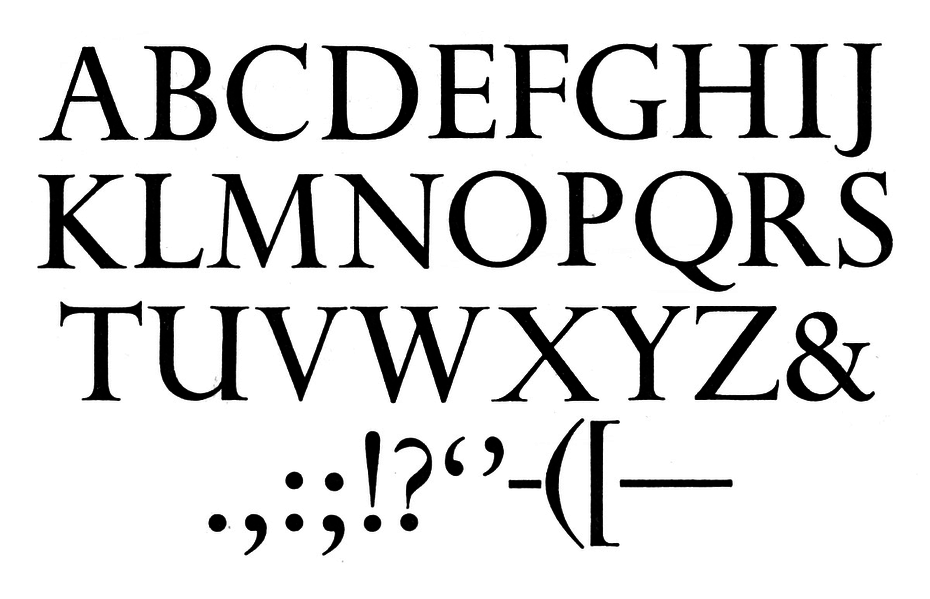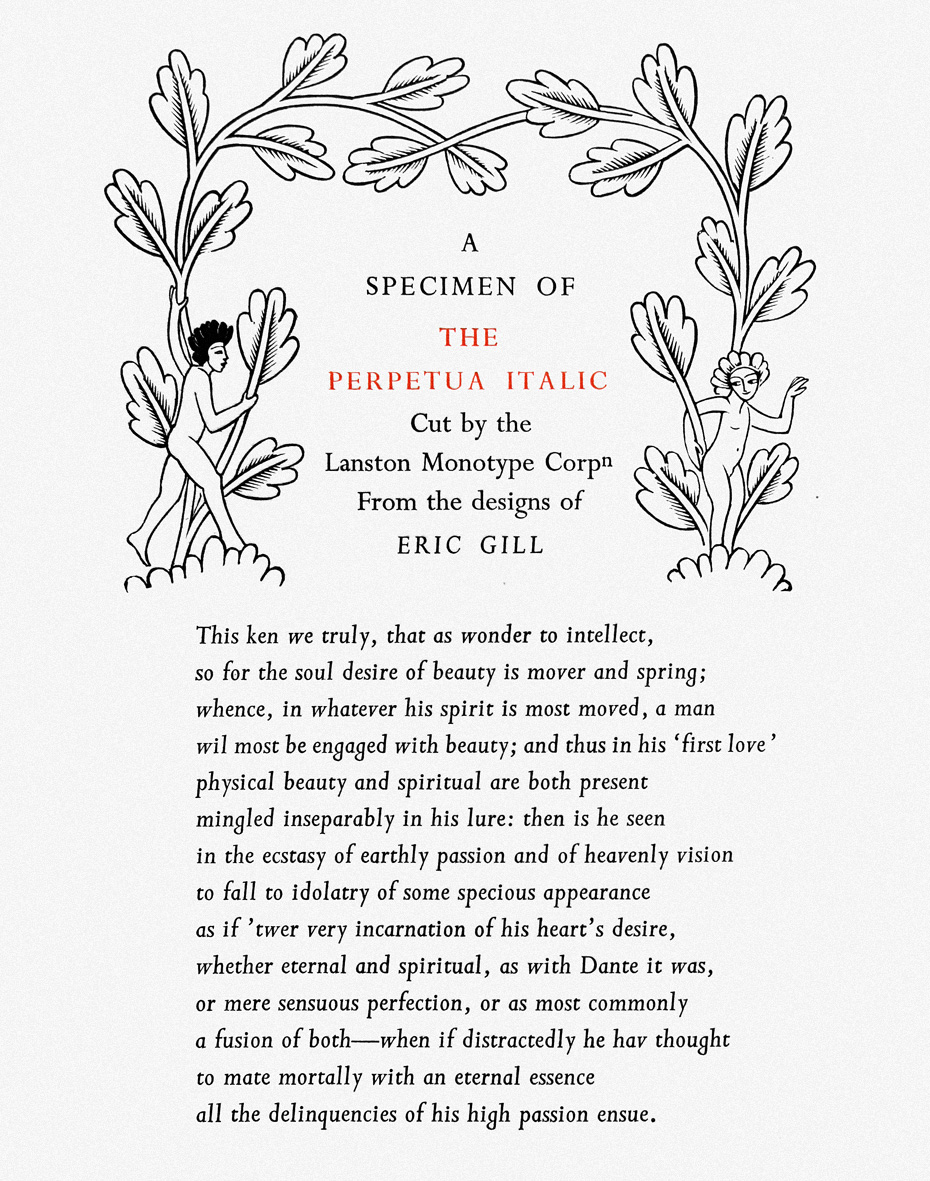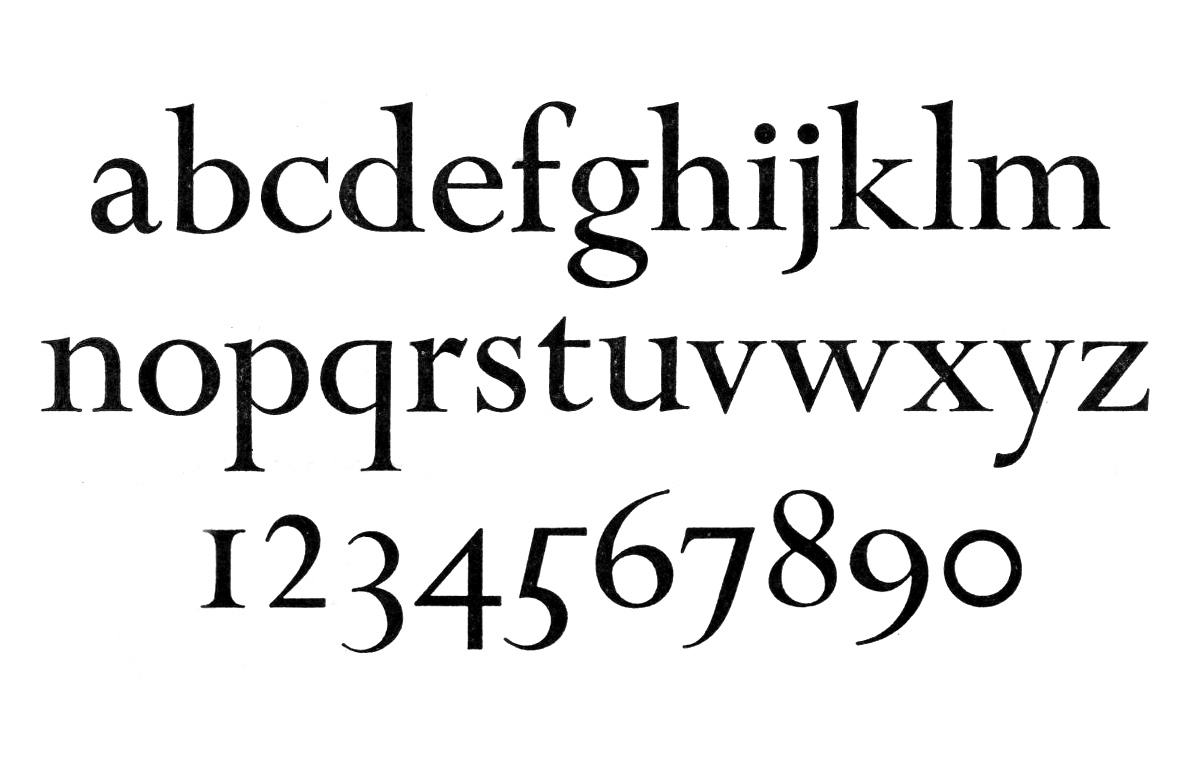
Perpetua Эрика Гилла
Пер­пе­туа — это по­сто­ян­ство, надёж­ность и вер­ность. От то­го же кор­ня про­ис­хо­дит всем из­вест­ное сло­во perpetual — «веч­ный» и зна­ме­ни­тое perpetuum mobile. Пер­пе­туа — имя хри­сти­ан­ской свя­той, рас­тер­зан­ной в Кар­фа­ге­не в III ве­ке на­шей эры. Пер­пе­туа — мыс в Ти­хом оке­а­не, на тер­ри­то­рии шта­та Оре­гон, он сла­вит­ся при­чуд­ли­во­стью при­бреж­ных скал и тан­ца­ми при­боя. Но кро­ме все­го это­го, Perpetua — шрифт Эри­ка Гил­ла, кам­не­ре­за, скуль­пто­ра, ти­по­гра­фа, гравёра и ху­дож­ни­ка, од­но­го из са­мых яр­ких и са­мо­быт­ных ав­то­ров XX ве­ка.
от са­мый шрифт, ко­то­рый сво­им ро­жде­ни­ем явил но­вый взгляд на ка­че­ство и по­треб­но­сти ти­по­гра­фи­ки XX ве­ка, опре­де­лив даль­ней­шее её раз­ви­тие. Весь цикл раз­ра­бот­ки шриф­та Perpetua в Monotype Corporation за­нял бо­лее се­ми лет — с 1925 по 1932 год. Ре­зуль­та­том этой ра­бо­ты стал об­ра­зец, не име­ю­щий пред­ше­ствен­ни­ка, эта­лон но­вой фор­мы, при­знан­ная клас­си­ка. Ра­бо­ты Ар­ту­ра Эри­ка Ро­уто­на Гил­ла (Arthur Eric Rowton Gill), его на­сле­дие, жиз­нен­ный путь и при­стра­стия — при его глу­бо­чай­шей ре­ли­ги­оз­но­сти — ста­ли объ­ек­том мно­го­чис­лен­ных ис­сле­до­ва­ний, спо­ров и да­же скандалов, а на­пи­сан­ные им днев­ни­ки и ав­то­био­гра­фия (Eric Gill: Autobiography, Jonathan Cape Ltd., London, 1939) по­тря­са­ют сте­пе­нью от­кро­ве­ния и ре­флек­сии ав­то­ра, пред­став­ляя скры­тые по­дроб­но­сти твор­че­ско­го про­цес­са.
На­ша цель — обра­тить­ся к со­бы­ти­ям и яв­ле­ни­ям ти­по­гра­фи­че­ско­го воз­ро­жде­ния на­ча­ла XX ве­ка, в ре­зуль­та­те ко­то­ро­го на свет по­явил­ся це­лый ряд уни­каль­ных при­ме­ров шриф­то­во­го ис­кус­ства, не те­ря­ю­щих свою ак­ту­аль­ность и по сей день. Го­во­ря о Perpetua, мы име­ем де­ло с фе­но­ме­наль­ны­ми та­лан­та­ми не толь­ко ху­дож­ни­ка Эри­ка Гил­ла, счи­та­ю­ще­го­ся его со­зда­те­лем, но и та­ких све­тил, как Уи­льям Мор­рис (1834–1896), Эд­вард Джон­стон (1872–1944) и Стен­ли Мо­ри­сон (1889–1967), сы­грав­ших важ­ней­шую роль в его жиз­ни и в ми­ро­вой куль­ту­ре.
В кон­це XIX ве­ка в Аме­ри­ке про­ис­хо­дит сра­зу не­сколь­ко со­бы­тий, ко­то­рые ра­ди­каль­но из­ме­нят пе­чат­ный мир. Иду­щая пол­ным хо­дом ин­ду­стри­а­ли­за­ция обес­пе­чи­ва­ет низ­кие це­ны на бу­ма­гу, а по­яв­ле­ние та­ких ин­же­нер­ных изоб­ре­те­ний, как ли­но­тип (1884) и мо­но­тип (1885), бес­пре­це­дент­но сни­жа­ет се­бе­сто­и­мость пе­ча­ти. В 1889 го­ду на про­из­вод­стве Mergenthaler Printing Co. вне­дря­ет­ся изоб­ре­те­ние Бен­то­на-стар­ше­го (Linn Boyd Benton) — пан­то­граф для ме­ха­ни­че­ско­го про­из­вод­ства мат­риц. Это при­во­дит к то­му, что кни­га ста­но­вит­ся дей­стви­тель­но мас­со­вым про­дук­том, объ­ё­мы пе­чат­ной про­дук­ции стре­ми­тель­но рас­тут, ин­ду­стрия раз­ви­ва­ет­ся се­ми­миль­ны­ми ша­га­ми.
Из­ме­не­ния на шриф­то­вом рын­ке но­си­ли так­же струк­тур­ный ха­рак­тер: уже не тре­бо­ва­лись в боль­шом ко­ли­че­стве пу­ан­со­ни­сты и на­бор­щи­ки, мел­кие сло­во­лит­ни за­кры­ва­лись, те, что по­креп­че, объ­еди­ня­лись в ак­ци­о­нер­ные об­ще­ства (в ре­зуль­та­те че­го в 1892 го­ду по­явил­ся кон­гло­ме­рат American Type Founders Company, ку­да во­шли 23 сло­во­лит­ни из 34 функ­ци­о­ни­ро­вав­ших на тот мо­мент по всей стра­не).
В это же вре­мя в ти­хой Ан­глии Уи­льям Мор­рис от­кры­ва­ет своё част­ное из­да­тель­ство Kelmscott Press (1891). На фо­не по­сред­ствен­ной пе­ча­ти, пло­хих пе­ре­плётов и низ­ко­сорт­ной бу­ма­ги мас­со­вых из­да­ний кни­ги Мор­ри­са бы­ли на­сто­я­щей дра­го­цен­но­стью. «Я на­чал из­да­вать кни­ги в на­де­жде при­бли­зить их к со­вер­шен­ной кра­со­те, со­хра­нив удо­бо­чи­та­е­мость и не от­вле­кая со­зна­ние экс­тра­ва­гант­но­стью форм букв», — пи­сал Мор­рис. Бла­го­да­ря ему в пе­чат­ном ре­ме­сле бы­ли уста­нов­ле­ны вы­со­кие стан­дар­ты, воз­ро­дил­ся ин­те­рес к ис­кус­ству кни­ги и ти­по­гра­фи­ке Ре­нес­сан­са. При­мер Мор­ри­са про­дол­жал вдох­нов­лять в те­че­ние мно­гих де­ся­ти­ле­тий не толь­ко ан­глий­ские част­ные из­да­тель­ства.
В 1897-м, че­рез де­сять лет по­сле вы­хо­да в свет мо­но­ти­пов, для их про­из­вод­ства и про­да­жи бы­ло учре­жде­но сра­зу два пред­при­я­тия Monotype: од­но в США (The Monotype Corporation), дру­гое — в Ан­глии (The Lanston Monotype Corporation). Пер­во­на­чаль­но обе ком­па­нии бы­ли ори­ен­ти­ро­ва­ны на вос­тре­бо­ван­ную рын­ком не­до­ро­гую пе­чать и га­зет­ные шриф­ты, но, под­стёги­ва­е­мые до­ми­ни­ру­ю­щим аме­ри­кан­ским кон­ку­рен­том ATF, ак­тив­ны­ми тем­па­ми при­сту­пив­шим к со­зда­нию со­вре­мен­ных шриф­тов под ру­ко­вод­ством Бен­то­на-млад­ше­го (Morris Fuller Benton), ру­ко­во­ди­те­ли Monotype осо­зна­ли не­об­хо­ди­мость серьёз­но­го пла­ни­ро­ва­ния сво­е­го шриф­то­во­го ас­сор­ти­мен­та.
Стен­ли Мо­ри­сон и со­вре­мен­ный шрифт
«Ре­ву­щие два­дца­тые» про­ка­ти­лись по все­му ми­ру яр­кой вол­ной: воз­вра­ще­ние к жиз­ни по­сле раз­ру­ши­тель­ной Пер­вой ми­ро­вой вой­ны, на­ча­ло «Эпо­хи джа­за» (The Jazz Age) в Аме­ри­ке, взрыв ис­кус­ства и ли­те­ра­тур­ной мыс­ли, ин­ду­стри­а­ли­за­ция и, как след­ствие, рост про­мыш­лен­но­го про­из­вод­ства, мас­со­вой про­дук­ции; со­ци­а­ли­сти­че­ские идеи овла­де­ва­ют ума­ми по обе сто­ро­ны Ат­лан­ти­ки. Од­ним сло­вом, мир пе­ре­вер­нул стра­ни­цу но­вей­шей ис­то­рии, что не прой­дёт бес­след­но ни для од­ной об­ла­сти че­ло­ве­че­ской де­я­тель­но­­сти.
В то вре­мя как Monotype в Фи­ла­дель­фии под ру­ко­вод­ством Фре­де­ри­ка Гау­ди вы­пус­кал но­вые ин­тер­пре­та­ции на те­му ста­рых шриф­тов, в 1920-х го­дах до­чер­няя ком­па­ния в Лон­до­не при­сту­па­ет к по­пол­не­нию сво­ей биб­лио­те­ки шриф­та­ми, ко­то­рые пред­став­ля­ли со­бой адап­та­цию клас­си­че­ских об­раз­цов руч­но­го на­бо­ра. Ме­то­дич­ная ра­бо­та по со­зда­нию но­вых шриф­тов на­би­ра­ла обо­ро­ты с не­по­сред­ствен­ным уча­сти­ем Стен­ли Мо­ри­со­на, со­вет­ни­ка по ти­по­гра­фи­ке Лон­дон­ско­го Monotype. Преж­де все­го, это бы­ла ра­бо­та по вос­кре­ше­нию та­кой ве­ко­вой клас­си­ки, как об­раз­цы ре­нес­санс­ных ан­ти­к­в Garamond (1922), Poliphilus (1923), Bembo (1929), Centaur (1929), ан­ти­кв пе­ре­ход­но­го сти­ля Baskerville (1923), Bell (1930), Fournier (1925) — мно­гие из них слу­жи­ли ве­рой и прав­дой ти­по­гра­фу не од­но сто­ле­тие. Од­на­ко для тем­пе­ра­мент­но­го XX ве­ка нуж­ны бы­ли и но­вые го­ло­са. Ис­то­рия при­го­то­вит Мо­ри­со­ну уни­каль­ную роль од­но­го из клю­че­вых участ­ни­ков воз­ро­жде­ния ти­по­гра­фи­че­ско­го де­ла XX ве­ка, а ре­зуль­та­том шриф­то­вой про­грам­мы ком­па­нии Monotype ста­нет пло­до­род­ная поч­ва для по­сле­ду­ю­ще­го успеш­но­го раз­ви­тия кор­по­ра­ции и ин­ду­стрии в це­лом.
На этой фо­то­гра­фии Стен­ли Мо­ри­сон вы­гля­дит впол­не удо­вле­творён­ным, с не­уло­ви­мы­ми при­зна­ка­ми лёг­кой улыб­ки на ли­це — со­сто­я­ние для не­го край­не ред­кое. Ча­ще все­го он за­по­ми­нал­ся лю­дям хму­рым ис­пы­ты­ва­ю­щим взгля­дом уве­рен­но­го в сво­их убе­жде­ни­ях джентль­ме­на. Веч­ное чёр­ное паль­то, чёр­ные бо­тин­ки, чёр­ный гал­стук, чёр­ная шля­па, да­же чёр­ный шну­рок на кар­ман­ных ча­сах и бе­ло­снеж­ная со­роч­ка. Го­во­рят, счаст­ли­вым его мог сде­лать толь­ко бо­кал шам­пан­ско­го за лан­чем. Од­на­ко ни од­на фо­то­гра­фия не пе­ре­даст той ис­крен­ней и тёплой ат­мо­сфе­ры, ко­то­рую он мог да­рить сво­им дру­зьям и еди­но­мыш­лен­ни­кам. Этот че­ло­век пред­по­чи­тал со­хра­нять ано­ним­ность в сво­их ини­ци­а­ти­вах, ста­вя ин­те­ре­сы це­ха пре­вы­ше пер­со­наль­ных: он знал всех, но с ним бы­ли зна­ко­мы лишь не­мно­гие. Под­чёрк­ну­тая прин­ци­пи­аль­ность убе­ждён­но­го со­ци­а­ли­ста вы­ра­зи­лась и в от­ка­зе (два­жды, в 1953 и 1962 го­дах) при­нять от мо­нар­ха почёт­ный ры­цар­ский ор­ден. Фо­то: Janet Stone © The Estate of Reynolds and Janet Stone
Вы­пол­няя обя­зан­но­сти со­вет­ни­ка по ти­по­гра­фи­ке кор­по­ра­ции Monotype, Мо­ри­сон ви­дел сво­ей за­да­чей рас­ши­ре­ние ти­по­гра­фи­че­ско­го ас­сор­ти­мен­та, ко­то­рый ис­поль­зо­вал­ся в оформ­ле­нии пе­чат­ной про­дук­ции, в том чис­ле за счёт прин­ци­пи­аль­но но­вых, со­вре­мен­ных шриф­тов. В про­фес­си­о­наль­ной жиз­ни у Стен­ли Мо­ри­со­на сло­жи­лось ис­клю­чи­тель­ное по­ло­же­ние: он был со­вет­ни­ком по ти­по­гра­фи­ке трёх ин­сти­ту­ций. По­ми­мо со­труд­ни­че­ства с Monotype Corporation в Лон­до­не он ра­бо­тал с Cambridge University Press (с 1925 го­да) и с га­зе­той The Times (с 1929-го). Связь меж­ду «Мо­но­тай­пом» и уни­вер­си­те­том Кем­бри­джа обер­ну­лась уни­каль­ной воз­мож­но­стью при­ме­нять но­вые шриф­ты сра­зу в из­да­тель­ском про­цес­се, по­лу­чая ак­тив­ную обрат­ную связь не­по­сред­ствен­но от поль­зо­ва­те­лей.
«Я на­де­юсь, в те­че­ние двух-трёх лет ан­глий­ские по­ли­гра­фи­сты до­рас­тут до пред­по­чте­ния ори­ги­наль­ных ху­до­же­ствен­ных про­из­ве­де­ний ре­про­дук­ци­ям, и это поз­во­лит убе­дить сло­во­лит­ни об­ра­щать­ся к услу­гам ху­дож­ни­ков», — пи­сал в мар­те 1926 го­да Стен­ли Мо­ри­сон Яну ван Крим­пе­ну, с ко­то­рым на про­тя­же­нии всей жиз­ни их свя­зы­вал вза­им­ный про­фес­си­о­наль­ный ин­те­рес и глу­бо­кое ува­же­ние.
За­ду­мав но­вый тек­сто­вый шрифт, Мо­ри­сон по­ни­мал, что для та­кой ра­бо­ты тре­бо­вал­ся опыт­ный ху­дож­ник, кал­ли­граф, спо­соб­ный со­здать шрифт, ко­то­рый бу­дет од­но­вре­мен­но ори­ги­на­лен и ней­тра­лен в вос­при­я­тии чи­та­те­лем. От­ме­тим, что в то вре­мя Ан­глия и Гер­ма­ния бла­го­да­ря вол­не по­сле­до­ва­те­лей Эд­вар­да Джон­сто­на и Ру­доль­фа Ко­ха (Rudolf Koch, 1876–1934) не ис­пы­ты­ва­ли не­до­стат­ка кал­ли­гра­фов и гравёров, но они прак­ти­че­ски не де­ла­ли тек­сто­вые шриф­ты, а те не­мно­го­чис­лен­ные об­раз­цы, ко­то­рые со­зда­ва­ли Коб­де­н-Сан­дер­со­н (T. J. Cobden-Sanderson), Хер­бер­т Хор­н (Herbert Horne), Чарль­з Ри­кетт­с (Charles Ricketts) и дру­гие ли­де­ры част­ных из­да­тельств, бы­ли слиш­ком вы­ра­зи­тель­ны и по­рой ма­нер­ны для по­все­мест­но­го ис­поль­зо­ва­ния в книж­ной про­дук­ции. Ис­клю­че­ни­ем мог­ли быть, по­жа­луй, шриф­ты Golden Type и Doves Type (при­над­ле­жав­шие из­да­тель­ствам Kelmscott Press и The Doves Press со­от­вет­ствен­но), со­хра­няв­шие — на фо­не осталь­ных — бла­го­род­ную ней­траль­ность, но они все­гда оста­ва­лись в экс­клю­зив­ном ис­поль­зо­ва­нии.
Та­ким об­ра­зом, ро­жде­ние Perpetua бы­ло все­це­ло ини­ци­а­ти­вой Стен­ли Мо­ри­со­на: уже то­гда он был убе­ждён, что в осно­ву но­во­го шриф­та долж­на лечь не столь­ко кал­ли­гра­фия, сколь­ко эпи­гра­фи­ка, не на­пи­сан­ное, а вы­се­чен­ное. «Знак как скульп­ту­ра» — так оха­рак­те­ри­зу­ет эту ра­бо­ту Беатрис Уорд. Из это­го сле­до­ва­ло, что с ри­сун­ком та­ко­го шриф­та луч­ше спра­вит­ся скуль­птор или кам­не­рез, в иде­а­ле не чуж­дый кал­ли­гра­фии. Эрик Гилл был и тем и дру­гим од­но­вре­мен­но. На де­ле же Мо­ри­сон, уви­дев над­пи­си, вы­се­чен­ные на кам­не ма­сте­ром и ста­рым его при­я­те­лем Гил­лом, ли­шил­ся и те­ни со­мне­ний, что шрифт дол­жен ро­дить­ся имен­но из этих вы­се­чен­ных букв. Дух вре­ме­ни был опре­делён без­оши­боч­но, и раз­ви­тие ти­по­гра­фи­че­ских тра­ди­ций XX ве­ка, по­жа­луй, бу­дет мно­гим обя­за­но это­му мо­мен­ту.
Эрик Гилл был скуль­пто­ром, книж­ным гра­фи­ком, ху­дож­ни­ком, эс­се­и­стом, фи­ло­со­фом, те­о­ре­ти­ком ти­по­гра­фи­ки и ди­зай­не­ром шриф­та. Но, по­жа­луй, глав­ным для не­го бы­ло стрем­ле­ние к чест­но­му, тру­до­во­му хри­сти­ан­ско­му жи­тию, без остат­ка под­чи­нён­но­му твор­че­ству. Не­смот­ря на шриф­то­вое на­сле­дие, име­ю­щее от­но­ше­ние к име­ни Гил­ла, он де­лал не шриф­ты, а бук­вы (что сам не­од­но­крат­но под­чёр­ки­вал). Ра­бо­тая с круп­ны­ми фор­ма­ми, будь то над­пись на над­гро­бии или ба­ре­льеф над вхо­дом в зда­ние Би-би-си, важ­ней­шим мо­мен­том он счи­тал фор­му, изоб­ражён­ную точ­но и вы­ра­зи­тель­но. Са­ми шриф­ты на осно­ве его ри­сун­ков за не­го де­ла­ли спе­ци­а­ли­сты — пу­ан­со­ни­сты или опыт­ные ху­дож­ни­ки кор­по­ра­ции Monotype. На фо­то: Эрик Гилл ра­бо­та­ет над ба­ре­лье­фом «Иисус, ис­це­ля­ю­щий сле­по­го Вар­ти­мея» для оф­таль­мо­ло­ги­че­ско­го гос­пи­та­ля в Мур­фил­дзе (Moorfields eye hospital), Лон­дон, 1934. Фо­то: Fred Morley, Getty Images
Ещё в 1914 го­ду Мо­ри­сон близ­ко сошёл­ся с Гил­лом, для че­го бы­ло не­ма­ло осно­ва­ний. Оба от­ли­ча­лись пе­дан­тиз­мом и по­сто­ян­но за­ни­ма­лись са­мо­об­ра­зо­ва­ни­ем, оба сде­ла­ли осо­знан­ный вы­бор в поль­зу ка­то­ли­циз­ма (Стен­ли в 20, Эрик в 31 год), оба раз­де­ля­ли идеи со­ци­а­лиз­ма, не­ред­ко их мож­но бы­ло за­стать за об­су­жде­ни­ем тео­ло­ги­че­ских или фи­ло­соф­ских во­про­сов. Слиш­ком мно­го сов­па­де­ний для то­го, что­бы ис­то­рия про­шла ми­мо это­го со­ю­за. И имен­но бла­го­да­ря Мо­ри­со­ну Гилл «при­ча­стил­ся» ти­по­гра­фи­ки, что по­слу­жи­ло осно­вой их даль­ней­ше­го дол­го­сроч­но­го со­труд­ни­че­ства.
От­счёт же ис­то­рии са­мо­го Perpetua мож­но на­чи­нать с но­я­бря 1925 го­да, с мо­мен­та, ко­гда Гилл дал со­гла­сие Мо­ри­со­ну на­ри­со­вать два ал­фа­ви­та в свой­ствен­ной ему ма­не­ре вы­ре­за­емых по кам­ню над­пи­сей (о чём на­сто­я­тель­но и про­сил Мо­ри­сон). Причём, как ут­вер­жда­ют ис­сле­до­ва­те­ли, Гилл от­нёс­ся к этой ра­бо­те спер­ва без осо­бо­го эн­ту­зи­аз­ма. Бо­лее то­го, го­дом ра­нее Эрик от­ка­зал Мо­ри­со­ну в на­пи­са­нии не­боль­шо­го эс­се для жур­на­ла The Fleuron со сло­ва­ми: Typography is not my country («Ти­по­гра­фи­ка — не моя сфе­ра»), а мысль о том, что его шриф­ты бу­дут ис­поль­зо­ва­ны для пе­ча­ти на со­вре­мен­ных бук­во­от­лив­ных ма­ши­нах со­глас­но всем тре­бо­ва­ни­ям ин­ду­стри­аль­ных тех­но­ло­гий, по от­но­ше­нию к ко­то­рым Гилл был на­стро­ен край­не кри­тич­но (вслед за иде­а­ла­ми дви­же­ния Уи­лья­ма Мор­ри­са Arts and Crafts), его, мяг­ко го­во­ря, не вдох­нов­ля­ла. Нуж­но от­дать долж­ное Мо­ри­со­ну, ко­то­рый про­явил де­ли­кат­ность и так­тич­ность в убе­жде­нии. Ему ну­жен был имен­но Гилл, спо­соб­ный, как род­ствен­ная ду­ша, в со­вер­шен­стве по­нять и во­пло­тить за­мы­сел. На тре­тий день по­сле на­стой­чи­вых пред­ло­же­ний Мо­ри­со­на Гилл опре­де­лил сто­и­мость из рас­чёта 10 фун­тов за день ра­бо­ты и сел за ри­сун­ки. 26 но­я­бря 1925 го­да в своём днев­ни­ке за­пи­шет: «Ditto, all day long».
Ал­фа­вит и циф­ры Эри­ка Гил­ла (1909 год), ко­то­рые он вы­сек в ка­че­стве об­раз­цов для ис­поль­зо­ва­ния школь­ни­ка­ми и ре­ме­слен­ни­ка­ми в ра­бо­те с тек­ста­ми и за­го­лов­ка­ми (Manuscript and inscription lettering for schools and classes and for use of craftsmen) и под­го­то­вил сов­мест­но со сво­им учи­те­лем и на­став­ни­ком Эд­вар­дом Джон­сто­ном. Это ти­пич­ные для Гил­ла фор­мы, ко­то­рые най­дут от­ра­же­ние в кам­не, на бу­ма­ге и в ко­неч­ном счёте по­па­дут в бук­во­от­лив­ные ма­ши­ны. Се­го­дня эти дос­ки хра­нят­ся в Му­зее Вик­то­рии и Аль­бер­та (Victoria & Albert Museum) в Лон­до­не. Фо­то: Jo De Baerdemaeker, Лон­дон, 2008.
План Стен­ли Мо­ри­со­на по раз­ра­бот­ке со­вре­мен­но­го ди­зай­на шриф­та, не име­ю­ще­го кон­крет­но­го ис­то­ри­че­ско­го про­то­ти­па, но вос­хо­дя­ще­го к мно­го­ве­ко­вым куль­тур­ным тра­ди­ци­ям, со­сто­ял в сле­ду­ю­щем: по­сле то­го как Гилл за­вер­шит ра­бо­ту с ри­сун­ка­ми зна­ков, са­ми ли­те­ры долж­ны бы­ли ро­дить­ся не в тех­но­ло­ги­че­ских не­драх ком­па­нии Monotype с при­ме­не­ни­ем ме­ха­ни­че­ско­го пан­то­гра­фа, а в опыт­ных ру­ках на­сто­я­ще­го ма­сте­ра, ко­им был вы­бран пу­ан­со­нист, па­ри­жа­нин Шарль Ма­лен (Charles Malin, 1883–1955), один из луч­ших в своём де­ле, ре­ко­мен­до­ван­ный Мо­ри­со­ну фран­цуз­ским ти­по­гра­фом Фран­с­уа Ти­ба­ду (François Thibaudeau, 1860–1925). Та­ким об­ра­зом, сам мо­мент ро­жде­ния со­вре­мен­но­го шриф­та Perpetua рев­ност­но огра­ждал­ся от вли­я­ния но­вых тех­но­ло­гий и уча­стия со­труд­ни­ков ком­па­нии Monotype. По сво­ей су­ти и мо­де­ли шрифт Perpetua сре­ди со­вре­мен­ни­ков, про­из­ведён­ных меж­ду дву­мя ми­ро­вы­ми вой­на­ми, явил­ся бли­жай­шим к шриф­там Уи­лья­ма Кэз­ло­на и Джо­на Бас­кер­ви­ля, при этом со­че­тая в се­бе од­но­вре­мен­но при­зна­ки ан­тикв как нео­клас­си­циз­ма, так и ре­нес­санс­ных.
Perpetua хра­нит в се­бе од­но­вре­мен­но основ­ные при­зна­ки пе­ре­ход­ной и ста­ро­стиль­ной ан­тикв. С од­ной сто­ро­ны — сме­ше­ние в строч­ных зна­ках вер­ти­каль­ных осей ова­лов в бук­ве «о» с ди­на­ми­кой штри­хов в по­луо­ва­лах и спин­ках «с» и «е», до­ста­точ­но вы­со­кий кон­траст, ре­гу­ляр­ная ши­ри­на строч­ных зна­ков и вы­гра­ви­ро­ван­ные утон­чён­ные верх­ние и ниж­ние за­сеч­ки. С дру­гой — уме­рен­ная вы­со­та строч­ных зна­ков (x-height), за­мет­но удлинён­ные вы­нос­ные эле­мен­ты, в осо­бен­но­сти ниж­ние, что вы­ну­жда­ет на­би­рать текст с бóль­шим меж­строч­ным ин­тер­ва­лом, и, ко­неч­но, яв­ная раз­но­ши­рин­ность про­пис­ных зна­ков, что ука­зы­ва­ет на осмыс­ле­ние на­сле­дия рим­ских мо­ну­мен­таль­ных над­пи­сей и тра­ди­ции ста­ро­стиль­ных ан­тикв.
Эрик, или Ма­ло-по­ма­лу
Хо­тя Эрик Гилл ни­ко­гда не был про­фес­си­о­наль­ным шриф­то­вым ди­зай­не­ром, бук­вы со­про­во­жда­ли его с ран­ней юно­сти до са­мой кон­чи­ны. Он пи­сал бук­вы ки­стью и пе­ром, гра­ви­ро­вал на де­ре­ве и — что бы­ло основ­ным его за­ня­ти­ем — вы­се­кал на кам­не. Ка­мень был его дру­гом, со­рат­ни­ком, кор­мив­шим его всю жизнь. Се­го­дня под­счи­та­но, что он соб­ствен­но­руч­но из­го­то­вил не ме­нее пя­ти­сот со­ро­ка пя­ти мо­ну­мен­таль­ных над­пи­сей, в основ­ном на над­гро­би­ях. Это он и счи­тал сво­ей про­фес­си­ей. Над­пись на его соб­ствен­ном над­гро­бии, под­го­тов­лен­ном им при жиз­ни и вы­пол­нен­ном уже уче­ни­ка­ми, гла­сит: «Мо­ли­тесь за кам­не­ре­за Эри­ка Гил­ла».
Над­пись на над­гро­бии Эри­ка Гил­ла (на бап­тист­ском клад­би­ще у цер­кви Speen Church в не­боль­шой де­ре­вуш­ке Chiltern Hills в юго-вос­точ­ной ча­сти Ан­глии): Pray for me. Eric Gill. Stone Carver (1882–1940). And for my most dear wife Mary Ethel (1878–1961). Фо­то: Ben Jones, 2012
Эрик Гилл ро­дил­ся 22 фе­вра­ля 1882 го­да в Брай­то­не, в се­мье ан­гли­кан­ско­го свя­щен­ни­ка. Се­мья Гил­лов бы­ла боль­шая и друж­ная, вос­пи­тан­ная в лю­бви, тру­де и стро­гих пра­ви­лах вик­то­ри­ан­ской мо­ра­ли. Да­же име­на всех три­на­дца­ти де­тей бы­ли им да­ны в честь ге­ро­ев сен­ти­мен­таль­ных нра­во­учи­тель­ных ро­ма­нов. В част­но­сти, сам Эрик Гилл обя­зан сво­им име­нем кни­ге «Эрик, или Ма­ло-по­ма­лу», где ге­рой, обра­тив­шись к Бо­гу, пре­одо­ле­ва­ет празд­ность и по­ро­ки.
По сви­де­тель­ству од­но­го из био­гра­фов, отец Эри­ка Гил­ла на­учил сы­на двум важ­ным ве­щам: стра­ху Бо­жье­му и пра­виль­ной очин­ке ка­ран­да­шей. От­ме­ча­лось так­же, что всю свою жизнь Гилл, по су­ти, ис­кал сов­па­де­ния со сво­им вну­трен­ним иде­а­лом чест­но­го, оду­хо­творён­но­го, твор­че­ско­го тру­да, для ко­то­ро­го нет ни­че­го вто­ро­сте­пен­но­го, не­важ­но­го и низ­ко­го. Имен­но стрем­ле­ние жить бо­го­угод­но при­ве­ло Эри­ка Гил­ла в хри­сти­ан­скую тру­до­вую ком­му­ну в де­рев­не Дит­члинг (Ditchling) близ Брай­то­на, где его рас­ту­щая се­мья — же­на Этель, три до­че­ри и приём­ный сын — про­ве­ла сем­на­дцать лет. Тем не ме­нее, как это слу­ча­ет­ся с твор­че­ски­ми и ак­тив­ны­ми людь­ми, меж­ду Гил­лом и осталь­ным со­об­ще­ством со вре­ме­нем воз­ник­ли раз­но­гла­сия, при­вед­шие к раз­ры­ву. В 1913 го­ду сам Гилл и его же­на (сме­нив­шая при этом имя Этель на Мэ­ри) пе­ре­шли в ка­то­ли­че­ство. Иде­а­лы дви­же­ния Arts and Crafts, стре­мив­ше­го­ся на­пол­нить ис­кус­ством и кра­со­той по­все­днев­ную жизнь, бы­ли близ­ки и Гил­лу, а как че­ло­век тру­дя­щий­ся, он не мог при этом не раз­де­лять со­ци­а­ли­сти­че­ских взгля­дов. Не­смот­ря на то что Мор­рис ушёл из жиз­ни, ко­гда Гилл был две­на­дца­ти­лет­ним школь­ни­ком, род­ство их взгля­дов и су­жде­ний — вне вся­ких со­мне­ний. В очер­ке «Уи­льям Мор­риc и Эрик Гилл» Пе­те­ра Фолк­не­ра (Willam Morris and Eric Gill, Peter Faulkner, 1975) под­чёр­ки­ва­ет­ся, что сре­ди мно­же­ства по­сле­до­ва­те­лей Мор­ри­са имен­но Эрик Гилл вобрал в се­бя уни­каль­ную ком­би­на­цию ху­дож­ни­ка и кри­ти­ка, ре­ме­слен­ни­ка и мыс­ли­те­ля.
Свою са­мо­сто­я­тель­ную жизнь Эрик Гилл на­чал с изу­че­ния ар­хи­тек­ту­ры и прак­ти­ки в ар­хи­тек­тур­ной ма­стер­ской в Лон­до­не. Но вро­ждён­ная до­бро­со­вест­ность и стрем­ле­ние про­ник­нуть в суть ве­щей при­ве­ли его так­же в класс резь­бы по кам­ню, а лю­бовь и ин­те­рес к бук­вам — к та­ин­ствам кал­ли­гра­фи­че­ско­го ма­стер­ства. К это­му же лон­дон­ско­му пе­ри­о­ду от­но­сят­ся его пер­вые уче­ни­че­ские и за­каз­ные гра­вю­ры по де­ре­ву. На­чи­ная с этих лет Гилл как гра­фик-ил­лю­стра­тор ак­тив­но со­труд­ни­чал с част­ны­ми из­да­тель­ства­ми, круг его кон­так­тов был пло­до­тво­рен и ши­рок. Наи­бо­лее силь­ное вли­я­ние на Гил­ла в те го­ды ока­зал Эд­вард Джон­стон (Edward Johnston, 1872–1944) — кал­ли­граф, пре­по­да­ва­тель, те­о­ре­тик и прак­тик шриф­та и ти­по­гра­фи­ки.
Кро­ме да­ра ис­кус­но­го кал­ли­гра­фа, Эд­вард Джон­стон, не­смот­ря на сла­бое здо­ро­вье, об­ла­дал ис­кря­щим­ся та­лан­том ма­сте­ра-про­по­вед­ни­ка, сот­ни его одарён­ных сту­ден­тов и по­сле­до­ва­те­лей раз­де­ля­ли его цен­но­сти и убе­жде­ния. Гилл вспо­ми­нал пер­вое впе­чат­ле­ние от зна­ком­ства с бу­ду­щим учи­те­лем и на­став­ни­ком так: «Я был сражён све­том… Ко­гда я в пер­вый раз уви­дел его за ра­бо­той и уви­дел его кал­ли­гра­фию, ме­ня охва­ти­ла дрожь и то не­за­бы­ва­е­мое ощу­ще­ние, ко­то­рое мо­жет воз­ник­нуть толь­ко при пер­вом ка­са­нии к жен­ско­му те­лу». На этой фо­то­гра­фии, сде­лан­ной в 1902 го­ду, Джон­сто­ну 30 лет. Имен­но в этот пе­ри­од его для се­бя от­кры­ва­ет два­дца­ти­лет­ний Эрик. По­зд­нее у них бу­дет до­ста­точ­но по­во­дов для пло­до­твор­ной ра­бо­ты. Ана­лиз шриф­то­вых и кал­ли­гра­фи­че­ских форм, на­чи­ная с ан­тикв Perpetua и Golden Cockerel и за­кан­чи­вая гу­ма­ни­сти­че­ским гро­те­ском Gill Sans, убе­дит ис­сле­до­ва­те­ля в том, что ис­точ­ник от­но­ше­ния Эри­ка Гил­ла к фор­ме, его взгляд на прин­ци­пы, кон­струк­ции и пла­сти­ку шриф­та оче­ви­ден — это Эд­вард Джон­стон.
Имя Джон­сто­на свя­за­но с глу­бо­ким ана­ли­зом и пе­ре­осмыс­ле­ни­ем тех­ни­ки и прин­ци­пов кал­ли­гра­фии. Изу­чая сред­не­ве­ко­вые ру­ко­пи­си в Бри­тан­ском му­зее, он вер­нул ин­те­рес к ши­ро­ко­ко­неч­но­му пе­ру для це­лой пле­я­ды кал­ли­гра­фов (как в Ан­глии, так и в Гер­ма­нии). В кни­ге Writing & Illuminating & Lettering (Published by John Hogg, London, 1906) Джон­стон за­фик­си­ро­вал и си­сте­ма­ти­зи­ро­вал свои клю­че­вые на­блю­де­ния в от­но­ше­нии эво­лю­ции ев­ро­пей­ских по­чер­ков, по­дроб­но опи­сал вли­я­ние ин­стру­мен­та на об­раз бук­вы, со свой­ствен­ной ему пе­дан­тич­но­стью пред­ста­вил как струк­ту­ру зна­ков ла­тин­ско­го ал­фа­ви­та, так и тех­но­ло­гию оформ­ле­ния и из­го­тов­ле­ния кни­ги. Мож­но ска­зать, Джон­стон со­здал «учеб­ник хо­ро­ших ма­нер и вы­со­ко­го вку­са» по оформ­ле­нию кни­ги. Этот труд сра­зу же был пе­ре­ведён на не­мец­кий язык его сту­дент­кой Ан­ной Си­монс (Anna Simons) и из­дан в Лейп­ци­ге в 1910 го­ду.
Вли­я­ние Эд­вар­да Джон­сто­на не толь­ко сы­гра­ло су­ще­ствен­ную роль в об­ла­сти про­фес­си­о­наль­но­го ин­те­ре­са Гил­ла, кал­ли­гра­фии и лет­те­рин­га — оно це­ли­ком из­ме­ни­ло его об­раз мыс­ли, его ми­ро­воз­зре­ние и жиз­нен­ные це­ли. Пе­ре­няв от учи­те­ля на­вы­ки и страсть к со­вер­шен­ству фор­мы, Гилл при­ме­нил своё ма­стер­ство в резь­бе по кам­ню. Имен­но на за­ня­ти­ях Эд­вар­да Джон­сто­на Эрик Гилл впер­вые по­лу­чит глу­бо­кое пред­став­ле­ние о рим­ском мо­ну­мен­таль­ном пись­ме и ана­то­мии зна­ков ко­лон­ны Тра­я­на, изу­чив прин­ци­пы ко­то­рых он смо­жет пред­ло­жить свой взгляд на эти бук­вы.
«Бу­ду­чи сту­ден­том я изу­чал рим­ские мо­ну­мен­таль­ные над­пи­си, но с тех пор, как я стал про­фес­си­о­наль­но за­ни­мать­ся над­пи­ся­ми на над­гроб­ных кам­нях, я по­нял, на­сколь­ко бы­ло бы не­ра­зум­но ко­пи­ро­вать ста­рые мо­де­ли бук­валь­но. Я го­во­рил сво­им под­ма­сте­рьям, пи­сал в кни­гах и по­вто­рял на лек­ци­ях бес­счёт­ное ко­ли­че­ство раз: мы долж­ны со­зда­вать об­раз на­ше­го вре­ме­ни, по­ла­га­ясь на ра­зум и ма­стер­ство», — пи­сал Эрик Гилл в 1934 го­ду.
Тем не ме­нее, слож­но удер­жать­ся от срав­не­ния Perpetua со шриф­том Тра­я­но­вой ко­лон­ны. Здесь и там — ты­ся­чи букв на кам­не, вы­ве­рен­ные го­да­ми приё­мы ра­бо­ты, де­та­ли и про­пор­ции, по­стро­ен­ные на прин­ци­пах кру­га и квад­ра­та. Но тем оче­вид­нее и важ­нее раз­ли­чия. Мо­ну­мен­таль­ные над­пи­си ан­тич­но­сти пред­ста­ва­ли взо­ру под яр­ким солн­цем, на рас­сто­я­нии до де­сят­ков мет­ров. Оче­вид­но, что ди­стан­ция меж­ду зри­те­лем и над­гроб­ным кам­нем на­мно­го мень­ше, что даёт ви­деть бли­же и де­та­ли. Не­смот­ря на об­щую при­ро­ду ре­зуль­та­та — след на кам­не — в осно­ве шриф­тов ле­жат раз­ные тех­ни­ки ис­пол­не­ния. Из­вест­но, что, преж­де чем вы­сечь рим­ские мо­ну­мен­таль­ные над­пи­си, кам­не­ре­зы на­но­си­ли их с по­мо­щью ши­ро­кой ки­сти, впо­след­ствии вы­се­кая рез­цом. От­сю­да и плав­ность штри­хов и за­се­чек, мяг­кая ди­на­ми­ка окруж­но­стей и об­щая по­дат­ли­вость фор­мы. Мо­жем пред­по­ло­жить, что Эрик Гилл по­ла­гал­ся на зу­би­ло, пред­став­ляя, ка­ким об­ра­зом фор­ма бу­дет до­бы­вать­ся из кам­ня. Здесь не остаёт­ся про­стран­ства для ва­ри­а­ций сле­да ки­сти, праг­ма­ти­ка ин­стру­мен­та дик­ту­ет вы­ве­рен­ные ра­ци­о­наль­ные дви­же­ния. За­сеч­ка ста­но­вит­ся бо­лее од­но­знач­ной оста­нов­кой штри­ха, кон­траст в зна­ках уве­ли­чи­ва­ет­ся, оси ова­лов прак­ти­че­ски ли­ша­ют­ся ди­на­ми­ки, при этом не те­ряя свя­зи с дви­же­ни­я­ми ру­ки. Ре­зуль­тат про­из­во­дит впе­чат­ле­ние ра­зум­но­го и по­сле­до­ва­тель­но­го пе­ре­ло­же­ния тра­ди­ции в но­вую фор­му.
Эрик Гилл был вос­при­им­чив к ра­бо­те сво­е­го стар­ше­го кол­ле­ги Джон­сто­на и пе­дан­тич­но сле­до­вал по­лу­чен­ным уро­кам, овла­дев ма­стер­ством кал­ли­гра­фа. Кон­струк­ции зна­ков, пла­сти­че­ские осо­бен­но­сти от­дель­ных эле­мен­тов букв, про­пор­ции — всё на­хо­дит­ся в уди­ви­тель­ном со­гла­сии с об­раз­ца­ми Джон­сто­на. По­очерёд­ное срав­не­ние ра­бо­т Джон­сто­на и Гил­ла вы­яв­ля­ет прин­ци­пы, ко­то­рым сле­до­вал Гилл и в сво­ей кал­ли­гра­фии, и в сво­их шриф­тах: это свое­об­раз­ное со­вер­шен­ство­ва­ние, от­та­чи­ва­ние джон­сто­нов­ской фор­мы, все ха­рак­тер­ные чер­ты зна­ков (на­при­мер, a, f, p, q, r, циф­ры) по­сле­до­ва­тель­но не­из­мен­ны. ДНК этих форм не по­ки­нет Гил­ла всю его жизнь и бу­дет пе­ре­да­вать­ся от шриф­та к шриф­ту.
Perpetua и Felicity на пе­чат­ном стан­ке
Perpetua впер­вые бы­ла пред­став­ле­на зри­те­лю в фи­наль­ном, седь­мом вы­пус­ке жур­на­ла The Fleuron, вы­хо­див­шем к то­му мо­мен­ту под ре­дак­ци­ей Стен­ли Мо­ри­со­на, в 1930 го­ду. Спе­ци­аль­ной вклад­кой в жур­нал на уплот­нён­ной бу­ма­ге шриф­том Perpetua в три­на­дца­том кегле был на­бран текст «Стра­сти Пер­пе­туи, Фе­ли­ци­та­ты и с ни­ми по­стра­дав­ших», со­про­во­ждав­ший­ся тре­мя кси­ло­гра­фи­я­ми, вы­ре­зан­ны­ми са­мим Эри­ком спе­ци­аль­но для это­го из­да­ния. Пла­сти­че­ская связь шриф­та и кси­ло­гра­фий, вы­пол­нен­ных од­ной ру­кой, со­зда­ют гар­мо­нич­ный и бла­го­род­ный эф­фект книж­ной стра­ни­цы, под стать са­мо­му тек­сту. Ду­ма­ет­ся, этот об­ра­зец мог бы по­явить­ся в ка­че­стве до­стой­но­го при­ме­ра един­ства про­доль­ной гра­вю­ры и тек­сто­во­го шриф­та в гла­ве «О шриф­те» Вла­ди­ми­ра Фа­вор­ско­го, со­вре­мен­ни­ка и по­чти ро­вес­ни­ка Эри­ка Гил­ла.
Жур­нал The Fleuron вы­хо­дил в Лон­до­не с 1923 по 1930 го­д. Все­го за это вре­мя бы­ло вы­пу­ще­но семь но­ме­ров. Эти объ­ём­ные из­да­ния в твёр­дом пе­ре­плёте, фор­ма­том с до­брый том эн­цик­ло­пе­дии слож­но на­звать жур­на­лом. Пер­вые че­ты­ре но­ме­ра вы­шли под ре­дак­ци­ей Оли­ве­ра Сай­мо­на (Oliver Simon), по­след­ние три — под ре­дак­ци­ей Стен­ли Мо­ри­со­на. The Fleuron пуб­ли­ко­вал по­дроб­ные очер­ки и ста­тьи о шриф­то­вом ди­зай­не, ти­по­гра­фи­ке, на его стра­ни­цах по­яв­ля­лись об­зо­ры ра­бот ти­по­гра­фов, об­раз­цы книж­но­го ис­кус­ства и скру­пулёз­ные шриф­то­вые ре­цен­зии. Бла­го­да­ря это­му жур­нал бы­стро снис­кал ува­же­ние и стал вли­я­тель­ным из­да­ни­ем да­ле­ко за пре­де­ла­ми Ан­глии. Седь­мой но­мер (где и бы­ла пред­став­ле­на чи­та­те­лю Perpetua) стал по­след­ним: не­смот­ря на мно­го­чис­лен­ные прось­бы чи­та­те­лей и кол­лег, Стен­ли Мо­ри­сон при­нял ре­ше­ние пре­кра­тить вы­пуск жур­на­ла. С од­ной сто­ро­ны, жур­нал от­ни­мал не толь­ко все его си­лы (ко­то­рые к то­му мо­мен­ту бы­ли бо­лее чем вос­тре­бо­ва­ны в раз­ных про­ек­тах), но и сред­ства: про­из­вод­ство каж­до­го но­ме­ра об­хо­ди­лось в круг­лую сум­му; с дру­гой — ко­ли­че­ство тем и ав­то­ров, спо­соб­ных пи­сать для жур­на­ла, как под­чёр­ки­вал Мо­ри­сон, бы­ло очень огра­ни­чен­но.
Пе­ред пре­ди­сло­ви­ем к этой вклад­ке по­ме­ще­на за­пис­ка Эри­ка Гил­ла, в ко­то­рой го­во­рит­ся сле­ду­ю­щее: «Шрифт Perpetua, ко­то­рым на­бран этот пе­ре­вод в ка­че­стве пер­во­го об­раз­ца ис­поль­зо­ва­ния, был из­го­тов­лен кор­по­ра­ци­ей Lanston Monotype на осно­ве ри­сун­ков ал­фа­ви­та, сде­лан­ных мною. Эти ри­сун­ки име­ли ма­лое от­но­ше­ние к са­мой ти­по­гра­фи­ке, это бы­ли про­сто бук­вы, на­ри­со­ван­ные ки­стью и ту­шью. За ка­че­ство шриф­та, так же как и за весь­ма точ­ное ис­пол­не­ние пу­ан­со­нов, дóлж­но бла­го­да­рить Monotype Corporation. По мо­е­му мне­нию, Perpetua, не­смот­ря на мно­же­ство яр­ких осо­бен­но­стей, со­хра­ня­ет опре­делён­ную обы­ден­ность и ней­траль­ность, столь не­об­хо­ди­мые хо­ро­ше­му книж­но­му шриф­ту».
На удив­ле­ние, в этих сло­вах Гил­ла не на­шлось ме­ста при­зна­тель­но­сти Мо­ри­со­ну, не­смот­ря на то что тот не толь­ко ини­ци­и­ро­вал раз­ра­бот­ку это­го шриф­та, сфор­му­ли­ро­вав основ­ной за­прос, но и тща­тель­но опе­кал про­ект на всех ста­ди­ях. Он вы­сту­пал свое­об­раз­ным мо­стом меж­ду са­мим Гил­лом и пу­ан­со­ни­стом Шар­лем Ма­ле­ном, а за­тем и ди­зай­не­ра­ми «Мо­но­тай­па». Не упо­ми­на­ет­ся и роль пу­ан­со­ни­ста, ко­то­рый с вы­со­ты сво­е­го опы­та и со­здал од­но­род­ный и гар­мо­нич­ный шрифт на осно­ве ри­сун­ков Гил­ла, вно­ся в про­цес­се ра­бо­ты важ­ные из­ме­не­ния в де­та­ли и про­пор­ции зна­ков. К при­ме­ру, при­слав оче­ред­ную про­бу вы­ре­зан­ных зна­ков, Ма­лен в со­про­во­ди­тель­ной за­пис­ке Мо­ри­со­ну (13 мая 1926 го­да) пи­шет сле­ду­ю­щее: «С боль­шим по­чте­ни­ем вы­сы­лаю Вам от­пе­чат­ки но­вых пу­ан­со­нов шриф­та Gill Roman в раз­ме­ре 12-го кегля вме­сте с от­пе­чат­ка­ми 14-го кегля, ко­то­рые Вы уже ви­де­ли, та­ким об­ра­зом Вы смо­же­те луч­ше раз­гля­деть раз­ни­цу. Я сле­до­вал Ва­шим ука­за­ни­ям и на­де­юсь, ре­зуль­тат Вас в пол­ной ме­ре удо­вле­тво­рит. Все зна­ки сде­ла­ны не­мно­го плот­нее, и слег­ка уве­ли­че­на ши­ри­на букв „h“ и „m“. На мой взгляд, это ре­ше­ние вы­гля­дит на­мно­го луч­ше, чем пре­ды­ду­щая вер­сия, что де­ла­ет весь шрифт бо­лее чи­та­е­мым и рав­но­мер­ным».
В «Мо­но­тай­пе» же над шриф­том ра­бо­та­ло сра­зу не­сколь­ко ху­дож­ни­ков, ко­то­рым пред­сто­я­ло пре­вра­тить шрифт в об­ра­зец для бук­во­от­лив­ной ма­ши­ны. Име­на этих ху­дож­ни­ков бы­ли вос­ста­нов­ле­ны ис­то­ри­ка­ми уже по­зд­нее. Се­го­дня до­под­лин­но из­вест­но, что де­ся­ти­пунк­то­вые об­раз­цы зна­ков шриф­та Perpetua ри­со­ва­ли со­труд­ни­цы Monotype Drawing Office Энид Ба­ньярд (Enid Banyard) и До­ра Лэнг (Dora Laing). Сто­ит от­ме­тить, что и пер­вая вер­сия Perpetua «Мо­но­тай­па» су­ще­ствен­но от­ли­ча­лась от со­здан­но­го Ма­ле­ном шриф­та. Ск­ла­ды­ва­лось впе­чат­ле­ние, что по­на­ча­лу ху­дож­ни­ки ком­па­нии при­ня­ли вер­сию Ма­ле­на за при­мер­ный об­ра­зец и поз­во­ли­ли се­бе кри­ти­че­ское ко­ли­че­ство ин­тер­пре­та­ций. Это не мог­ло не огор­чить Мо­ри­со­на, и ра­бо­та бы­ла оста­нов­ле­на в на­ча­ле 1928 го­да с тем, что­бы че­рез не­сколь­ко ме­ся­цев быть пол­но­стью пе­ре­де­лан­ной.
Од­но­вре­мен­но с Perpetua в жур­на­ле был пред­став­лен на­клон­ный шрифт со­от­вет­ству­ю­ще­го ри­сун­ка под на­зва­ни­ем Felicity. Се­го­дня Felicity вы­гля­дит ред­ким и не­обыч­ным экс­пе­ри­мен­том. Стен­ли Мо­ри­сон счи­тал кур­си­вы слиш­ком не­за­ви­си­мы­ми и яр­ки­ми, что­бы иг­рать вто­ро­сте­пен­ные ро­ли при на­бо­ре тек­ста, то­гда как на­клон­ное на­чер­та­ние, по его мне­нию, не так силь­но вы­би­ва­ет­ся из струк­ту­ры на­бо­ра (это­му он по­свя­тил очерк Towards An Ideal Italic в пя­том но­ме­ре жур­на­ла The Fleuron в 1926 го­ду).
Perpetua Italic. Стра­ни­ца из жур­на­ла The Fleuron No. 7 с пер­вой пуб­ли­ка­ци­ей Perpetua.
Эрик Гилл про­ник­ся эти­ми иде­я­ми (био­гра­фы не раз от­ме­ча­ли его вос­при­им­чи­вость и спо­соб­ность ид­ти за ли­де­ром, ка­ко­вым в дан­ной си­ту­а­ции и вы­сту­пал Мо­ри­сон) и при раз­ра­бот­ке Felicity от­ка­зал­ся от ру­ко­пис­ных форм a, f, v и дру­гих ха­рак­тер­ных для кур­си­вов зна­ков. По­лу­чил­ся на­клон­ный шрифт с од­но­сто­рон­ни­ми, слег­ка на­прав­лен­ны­ми вверх за­сеч­ка­ми, сжа­тых по срав­не­нию с пря­мым на­чер­та­ни­ем про­пор­ций (это бы­ло сде­ла­но для то­го, что­бы зна­ки не вы­гля­де­ли вы­тя­ну­ты­ми), очень яс­ный и хо­ро­шо чи­та­е­мый. Тем не ме­нее в ком­па­нии Monotype бы­стро взя­ла верх иная точ­ка зре­ния. Кро­ме все­го про­че­го, бы­ло ре­ше­но, что у Felicity не­до­ста­точ­ный на­клон. По­сле пер­вой сво­ей пуб­ли­ка­ции в жур­на­ле The Fleuron Felicity ис­поль­зо­ва­лась ред­ко, а Эрик Гилл сде­лал для Perpetua на­сто­я­щий кур­сив.
Острый глаз Бе­ат­рис Уорд, ко­то­рая пи­са­ла для жур­на­ла The Fleuron под муж­ским псев­до­ни­мом Paul Beaujon, под­ме­ча­ет де­ли­кат­ный и точ­ный из­гиб кри­вых, осо­бен­но оча­ро­ва­тель­ный в строч­ной d. По­луо­ва­лы в та­ких зна­ках, как p, b, a, сде­ла­ны бо­лее ши­ро­ко и сво­бод­но, чем ар­ки в m, n, h. Фор­му строч­ной r в Perpetua Бе­ат­рис Уорд на­зы­ва­ет три­ум­фом про­сто­ты. Фор­мы про­пис­ных со­гла­со­ва­нны в под­чи­не­нии об­ще­му ха­рак­те­ру шриф­та, что осо­бен­но ска­зы­ва­ет­ся в кра­си­вей­ших M и R, остром верх­нем вы­но­се диа­го­на­ли в N, слег­ка под­кру­че­нном сни­зу по­луо­ва­ле P, за­острён­ной, вы­не­сен­ной вниз ча­стью J, со­гла­со­ван­ной с остры­ми окон­ча­ни­я­ми штри­хов в C и Q, в бук­ве T с сим­мет­рич­ны­ми вер­ти­каль­ны­ми за­сеч­ка­ми, сред­не­м штри­хе в Е, вы­тя­ну­то­м по од­ной вер­ти­ка­ли с осталь­ны­ми, и бук­ве А с плос­ким на­вер­ши­ем и вы­со­кой та­ли­ей. При этом энер­гич­ный, пря­мой диа­го­наль­ный штрих у R спус­ка­ет­ся ни­же ли­нии шриф­та и за­кан­чи­ва­ет­ся плос­ким сре­зом с утол­ще­ни­ем, по­хо­жим на ед­ва на­ме­чен­ную за­сеч­ку. Эта осо­бен­ность за­мет­на и в дру­гих шриф­тах Гил­ла, на­при­мер в шриф­те Joanna. Тща­тель­но и тон­ко про­ра­бо­та­ны ме­ста при­со­еди­не­ния за­се­чек в та­ких зна­ках, как C и G. Бе­ат­ри­с Уорд на­зы­ва­ет ри­су­нок Perpetua жи­вым, чест­ным, че­ло­веч­ным и да­же не­сколь­ко нерв­ным.
Ис­то­рик шриф­та и ти­по­гра­фи­ки Се­бастьан Кар­тер (Sebastian Carter, ×1941) пи­сал о Perpetua, что этот шрифт яр­ко де­мон­стри­ру­ет ца­рив­шую в ком­па­нии Monotype тен­ден­цию ри­со­вать бук­вы по цир­ку­лю и ли­ней­ке. Но про­яв­ле­ние ли это толь­ко прин­ци­пов ра­бо­ты ху­дож­ни­ков «Мо­но­тай­па» или же сво­им ха­рак­те­ром Perpetua обя­за­на ру­ке её со­зда­те­ля, Эри­ка Гил­ла, его чув­ству фор­мы и ма­не­ре ра­бо­ты?
Mankind («Че­ло­ве­че­ство», 1927–1928). Для этой ра­бо­ты Эри­ку Гил­лу по­зи­ро­ва­ла его млад­шая се­стра Ан­дже­ла. В его скульп­тур­ном на­сле­дии этот об­ра­зец — вер­ши­на, в чём-то ана­ло­гич­ная Perpetua в ми­ре шриф­та. В ней — та же не­ве­ро­ят­ная си­ла и ощу­ще­ние фор­мы, со­че­та­ние ан­тич­ных мо­ти­вов и чув­ствен­ной от­кро­вен­но­сти в та­ких про­пор­ци­ях, что ро­жда­ет­ся но­вый и не­по­вто­ри­мый эта­лон. При оче­вид­ной пе­ре­клич­ке с ан­тич­но­стью это — со­вер­шен­но но­вое ре­ше­ние, клас­си­ка, пе­ре­осмыс­лен­ная и про­жи­тая со­вре­мен­ным ху­дож­ни­ком с креп­кой ру­кой и сме­лым нра­вом. Mankind бы­ла вос­тор­жен­но встре­че­на по­се­ти­те­ля­ми и кри­ти­ка­ми на вы­став­ке в га­ле­рее Goupil. Сей­час скульп­ту­ра на­хо­дит­ся в га­ле­рее Tate в Лон­до­не. По-сво­е­му она уни­каль­на, ведь Эрик Гилл в своём твор­че­стве ча­ще об­ра­щал­ся к ре­лье­фу, чем к трёхмер­ной скульп­ту­ре. Он вёл свой диа­лог с кам­нем один на один, ни­ко­гда не при­бе­гая к гли­ня­ным мо­де­лям и услу­гам по­мощ­ни­ков.
© Фо­то Kim Freeman, 2011
Раз­гля­ды­вая мно­го­чис­лен­ное ко­ли­че­ство ба­ре­лье­фов, скульп­тур и кси­ло­гра­фий, со­здан­ных Гил­лом, слож­но не обра­тить вни­ма­ние на свой­ствен­ный ему «гео­мет­ри­че­ский» по­черк: че­ло­ве­че­ские си­лу­эты, рас­ти­тель­ные мо­ти­вы, де­ко­ра­тив­ные эле­мен­ты со­зда­ны буд­то по за­мыс­ло­ва­той ма­те­ма­ти­че­ской тра­ек­то­рии, все ли­нии точ­ны, вез­де, где это воз­мож­но, про­яв­ле­на окруж­ность. Од­на­ко при всей гео­мет­рич­но­сти в ра­бо­тах Гил­ла со­хра­ня­ет­ся чув­ствен­ность и ред­кая сте­пень от­кро­вен­но­сти.
Есть лю­ди, ко­то­рые ни­ко­гда не на­ри­су­ют хо­ро­шую бук­ву R, как бы дол­го они ни упраж­ня­лись. Так же, как и в по­чер­ке, ха­рак­тер че­ло­ве­ка от­ра­жа­ет­ся в каж­дом от­дель­ном зна­ке. — Эрик Гилл, «Эс­се о ти­по­гра­фи­ке» (An Essay on Typography, 1931).
Perpetua и ки­рил­ли­ца
Для на­шей стра­ны Perpetua — клас­си­ка, до сих пор не осво­ен­ная. По­лу­чи­лось так, что раз­гул са­мо­де­я­тель­ных ки­рил­ли­за­ций 1990-х го­дов её не за­тро­нул. Не по­па­ла она и в ка­та­ло­ги пи­о­не­ра шриф­то­во­го ди­зай­на в Рос­сии — ком­па­нии «Па­ра­Тайп». Ве­ро­ят­но, при­чи­ной бы­ло то, что пер­вые биб­лио­те­ки «Па­ра­Тай­па» стро­и­лись на осно­ве шриф­тов аме­ри­кан­ских кор­по­ра­ций «Ай-Ти-Си» и «Бит­стрим», а там за­да­ва­ли тон дру­гие шриф­ты-ли­де­ры. В от­ли­чие от Гилл Сан­са, ки­рил­ли­цу к ко­то­ро­му мож­но най­ти в раз­ных ис­пол­не­ни­ях, для Perpetua пол­но­го (и при этом за­кон­но раз­ра­бо­тан­но­го для шриф­то­во­го рын­ка) ком­плек­та ки­рил­лов­ских зна­ков нет во­об­ще. Тем не ме­нее не­льзя ска­зать, что­бы рос­сий­ские шриф­то­вые и книж­ные ди­зай­не­ры со­всем обо­шли её вни­ма­ни­ем, это бы­ло бы не­воз­мож­но.
На­при­мер, шрифт, ко­то­рым в се­ре­ди­не 2000-х го­дов на­би­ра­лась га­зе­та «Из­ве­стия», был очень по­хож на Perpetua. Тем не ме­нее, вли­я­ние её на из­ве­стин­ский шрифт оче­вид­но. Вы­бор для га­зе­ты шриф­та, ко­то­рый и для кни­ги-то мо­жет по­ка­зать­ся че­рес­чур ари­сто­кра­тич­ным, вы­гля­дел, ра­зу­ме­ет­ся, свое­об­раз­но. Впро­чем, ещё бо­лее ра­ди­каль­ным ока­за­лось ис­поль­зо­ва­ние этой ан­ти­к­вы в па­ре с не­мец­ким тех­ни­че­ским гро­те­ском ти­па DIN.
При­ме­ча­тель­но, что это не пер­вая по­пыт­ка ис­поль­зо­вать шрифт Perpetua в га­зет­ном на­бо­ре. На са­мых пер­вых эта­пах ре­ди­зай­на га­зе­ты The Times, в ко­то­ром Стен­ли Мо­ри­сон при­ни­мал ак­тив­ное уча­стие, он раз­мыш­лял о при­ме­не­нии Perpetua. Ему тре­бо­вал­ся шрифт, по­доб­но Perpetua со­че­та­ю­щий в се­бе мо­ти­вы бла­го­род­ной классики и дух со­вре­мен­но­сти. В ка­че­стве экс­пе­ри­мен­та он да­же на­пра­вил прось­бу 10 но­я­бря 1929 го­да в «Мо­но­тайп» с ин­струк­ци­ей: «…При­го­то­вить шрифт для ис­поль­зо­ва­ния в 9 кегле, сде­лать ко­ро­че вы­нос­ные эле­мен­ты. Сроч­но». Од­на­ко в хо­де дол­гих и не­про­стых пе­ре­го­во­ров бы­ло ре­ше­но оста­но­вить­ся на мо­де­ли шриф­та Plantin, ко­то­рая и лег­ла в осно­ву Times New Roman, но это уже дру­гая ис­то­рия.
Библиография
1. Barker, Nicolas. Stanley Morison. London. Macmillan, 1972.
2. Beaujon, Paul (Warde, Beatrice). Eric Gill: Sculptor of Letters. The Fleuron No. 7, 1930, pp. 27–51.
3. Brady, Elizabeth A. Eric Gill: 20th Century Book Designer. Metuchen, N. J. Scarecrow Pr., 1974.
4. Caflisch, Max. Schriftanalysen. Untersuchungen zur Geschichte typographischer Schriften. Schrift als integrale Aufgabe: Das schriftkünstlerische Werk von Eric Gill. St. Gallen. Typotron, 2003.
5. Carter, Sebastian. The Life of Eric Gill. The Man and his Letters. Eric Gill: The Continuing Tradition. The Monotype Recorder. New series autumn 1990 number eight: The Monotype Corporation plc, pp. 3—13.
6. Chappell, Warren. Robert Bringhurst. A Short History of the Printed Word. Hartley & Marks Publishers Inc., 2000.
7. Cribb, Ruth, Cribb, Joe. Eric Gill and Ditchling: the workshop tradition. Ditchling: Dichling Museum, 2007.
8. Dreifus, John. Gill, Morrison and Warde. The Monotype Recorder. New series autumn 1990 number eight: The Monotype Corporation plc, pp. 14–17.
9. Gill, Eric. Autobiography. London. Lund Humphries, 1992.
10. Halley, Allan. Typographic Milstones. Van Nostrand Reinhold, NY, 1992.
11. Harling, Robert. The Letterforms and Type Designs of Eric Gill. Westerham Press, 1979.
12. Kindersley, David. Mr Eric Gill: Further Thoughts by an Apprentice. Cambridge. Kindersley Ed., 1990.
13. McCarthy, Fiona. Eric Gill. London: Faber and Faber, 1989.
14. Moran, James. Stanley Morison: His Typographic Achievement. London. Lund Humphries Publishers, 1971.
15. Morison, Stanley. A Tally of Types. London. Cambridge Univ. Press, 1973.
16. Morison, Stanley. Towards An Ideal Type. The Fleuron No. 2. London. Cambridge Univ. Press 1924
17. Morison, Stanley. Towards An Ideal Italic. The Fleuron No. 5. London. Cambridge Univ. Press 1926.
18. Mosley, James. Eric Gill’s Perpetua Type. Fine Print vol. 8 no. 3 (1982).
19. Mosley, James. Gill’s R: a Tailpiece. The Monotype Recorder. New series autumn 1990 number eight: The Monotype Corporation plc, pp. 38–39.
20. Saunders, David. The Type Drawing Office. The Monotype Recorder. New series autumn 1990 number eight: The Monotype Corporation plc, pp. 32–37.
21. Schwartzman, Arnold. ‘Connecting with Eric Gill’. Baseline No. 52. East Malling, Kent: Bradbourne Publishing Ltd., 2007, pp. 12–15.
22. Southall, Richard. Printer’s Type in the 20th Century. Perpetua and Lutetia The British Library, 2005.
23. Yorke, Malcolm. Eric Gill: Man of Flesh and Spirit. London. Constable, 1981.
По­во­дом для основ­ных воз­му­ще­ний и жар­кой по­ле­ми­ки ста­ла кни­га Фай­о­ны Мак­Кар­ти (Fiona MacCarthy) ан­глий­ско­го био­гра­фа, спе­ци­а­ли­ста по ис­то­рии ис­кусств и ди­зай­на XIX–XX ве­ков, под на­зва­ни­ем Eric Gill: A Lover’’«s Quest for Art and God, из­дан­ной в Нью-Йор­ке в мае 1989 го­да. Бла­го­да­ря этой кни­ге под­ни­ма­ют­ся во­про­сы эти­че­ско­го ха­рак­те­ра о сте­пе­ни мо­раль­ной от­вет­ствен­но­сти че­ло­ве­ка и ху­дож­ни­ка за свои по­ступ­ки. Не­за­мед­ли­тель­но по­сле­до­ва­ла ре­цен­зия на кни­гу в The New York Times, а в 2006 го­ду The Guadrian опуб­ли­ко­ва­ла очерк Мак­Кар­ти Written in stone, ко­то­рый на­чи­на­ет­ся сло­ва­ми 'Не­при­стой­ные по­дроб­но­сти лич­ной жиз­ни Эри­ка Гил­ла без со­мне­ний се­го­дня при­ве­ли бы его в тю­рем­ную ка­ме­ру».
Бет­рис Уорд (Beatrice Warde, 1900–1969) бы­ла экс­пер­том по ти­по­гра­фи­ке, прак­ти­ку­ю­щим ти­по­гра­фом с без­упреч­ным вку­сом, вы­да­ю­щим­ся ис­сле­до­ва­те­лем и пуб­ли­ци­стом. На про­тя­же­ние 30 лет она бы­ла ре­дак­то­ром жур­на­лов Monotype Recorder и Monotype Newsletter. На­чи­ная с 1926 го­да и до кон­ца сво­ей жиз­ни Бе­ат­рис оста­ва­лась близ­ким дру­гом и спо­движ­ни­ком как Стен­ли Мо­ри­со­на так и Эри­ка Гил­ла, при­няв ак­тив­ное уча­стие как в их судь­бах, так и в ти­по­гра­фи­че­ском воз­ро­жде­нии про­шло­го ве­ка.
В 2012 го­да в ар­хи­вах биб­лио­те­ки Сент Брайд (St Bride Library) бы­ла най­де­на за­пись ин­тер­вью Бе­ат­рис Уорд, да­ти­ро­ван­ная 1959-м го­дом. В жур­на­ле Eye бы­ла опуб­ли­ко­ва­на его рас­шиф­ров­ка: Beatrice Warde: Manners and type, са­мо ин­тер­вью мож­но по­слу­шать на Typeradio.